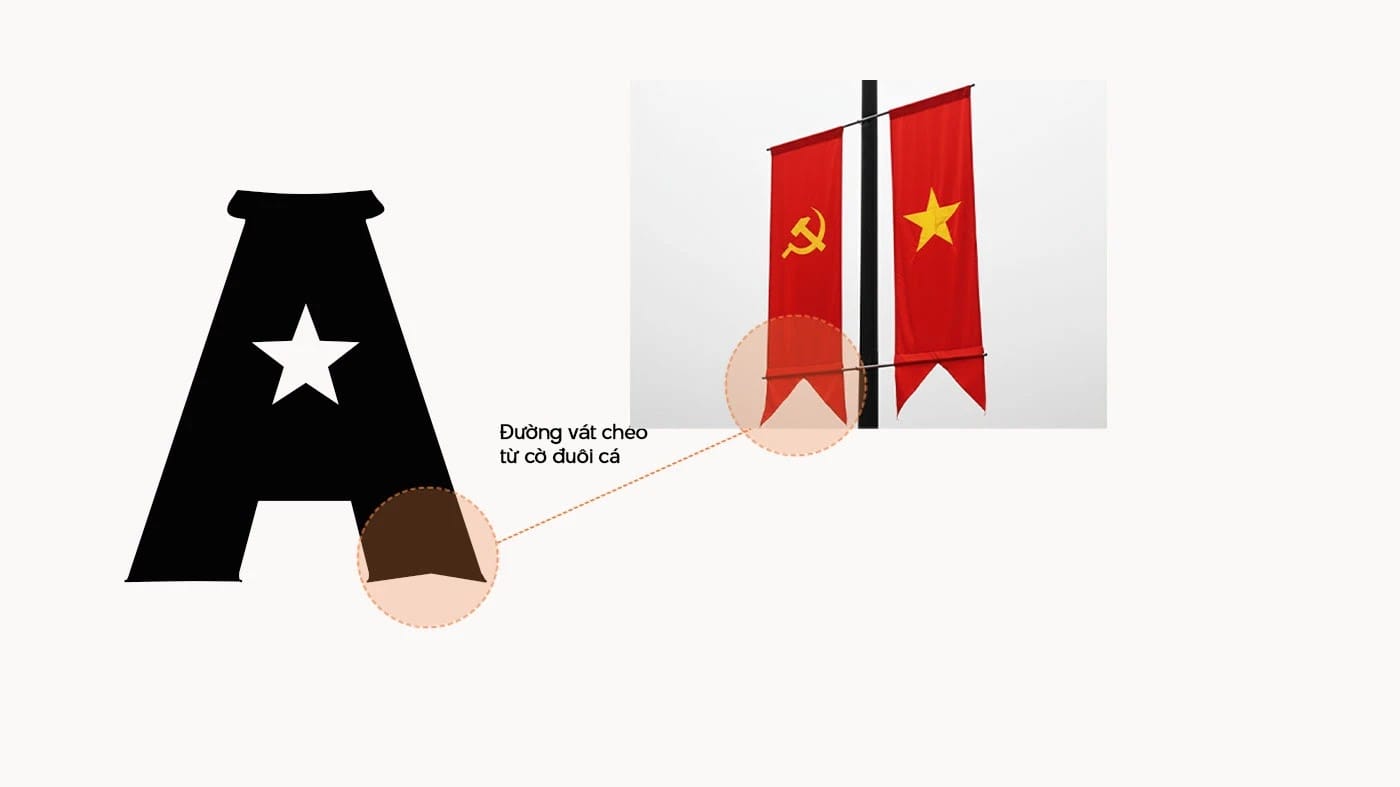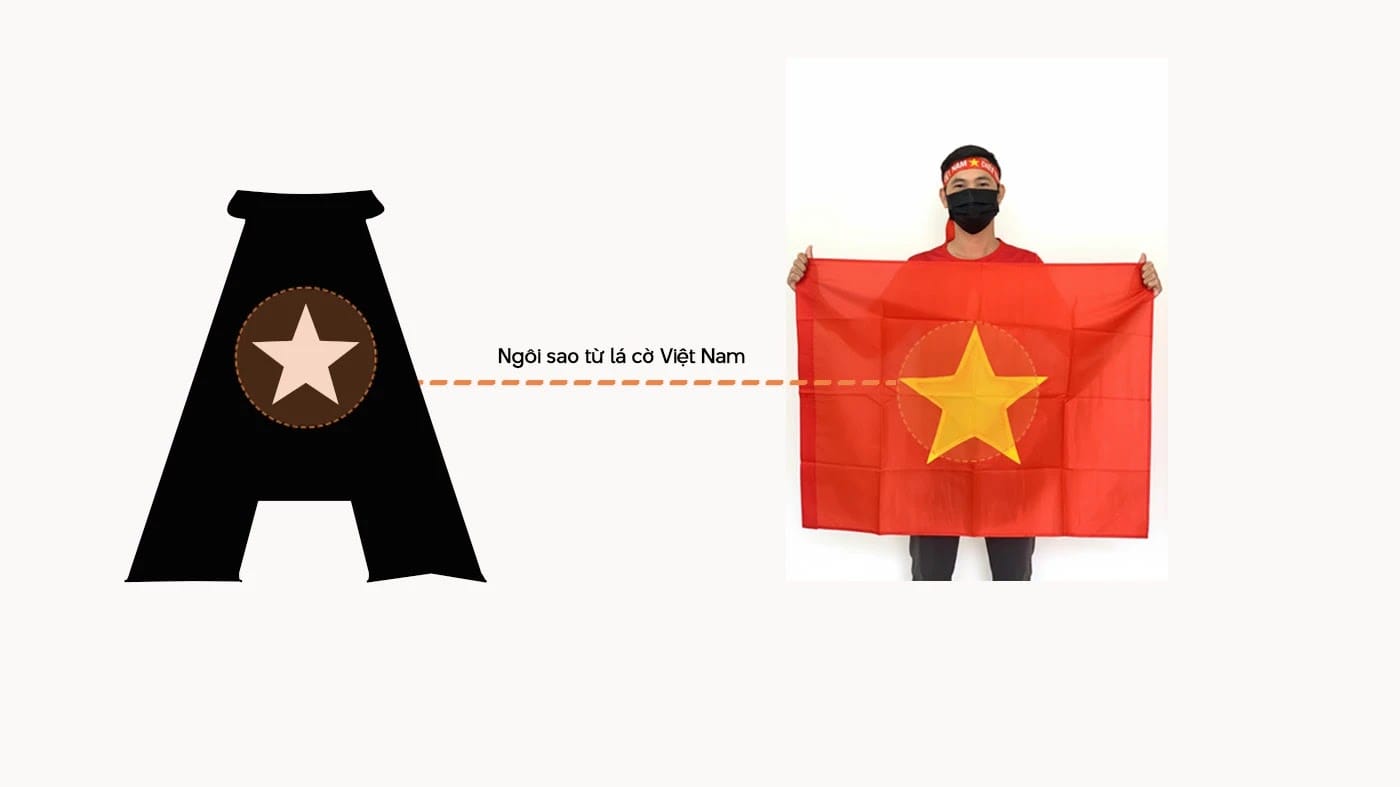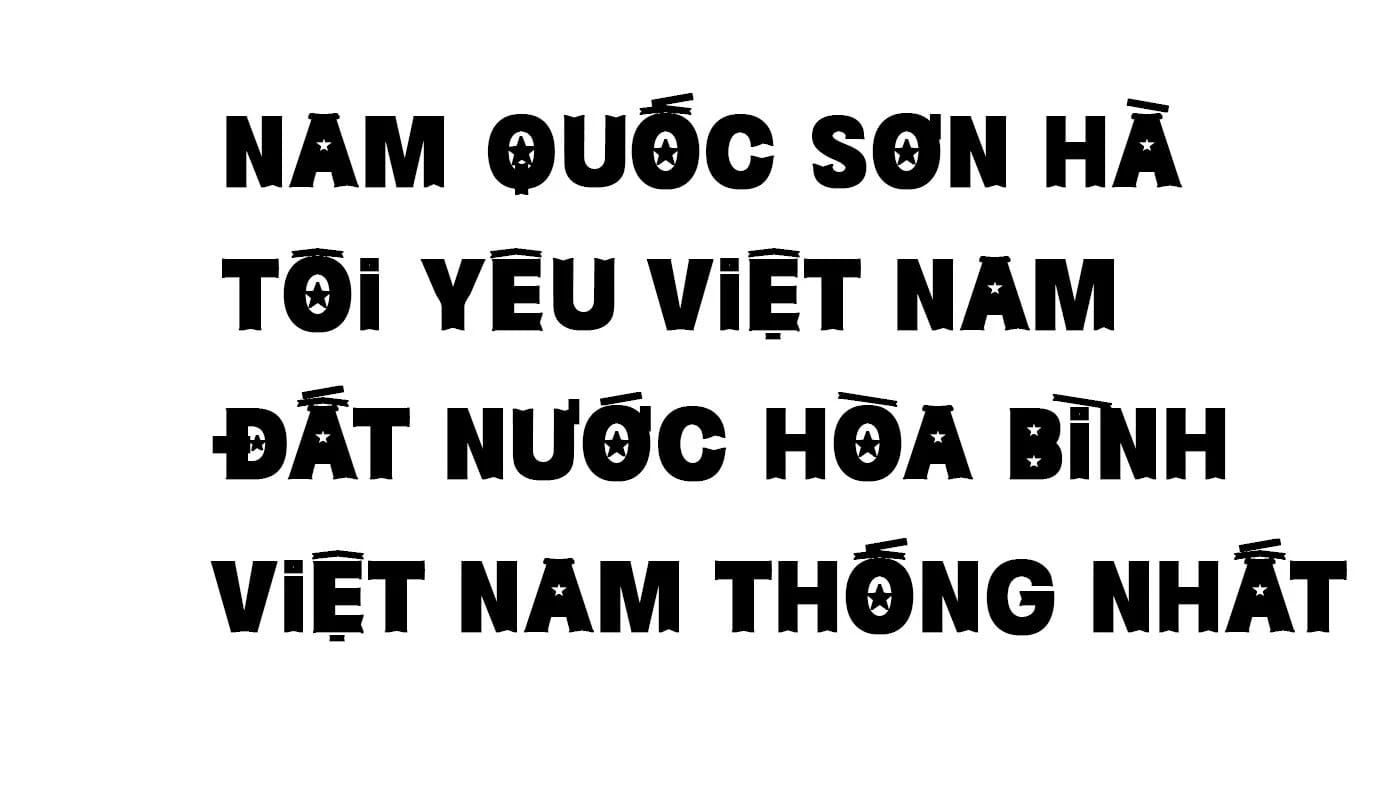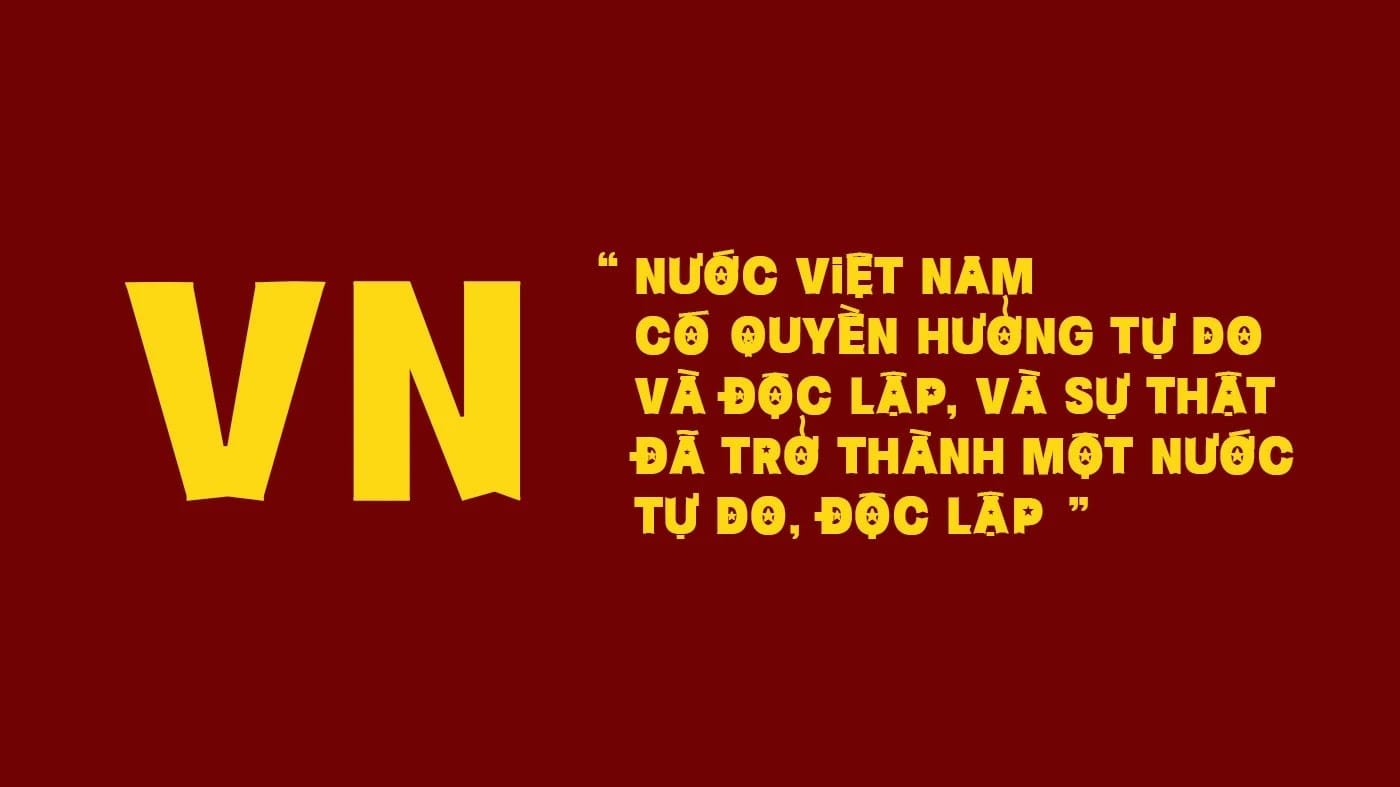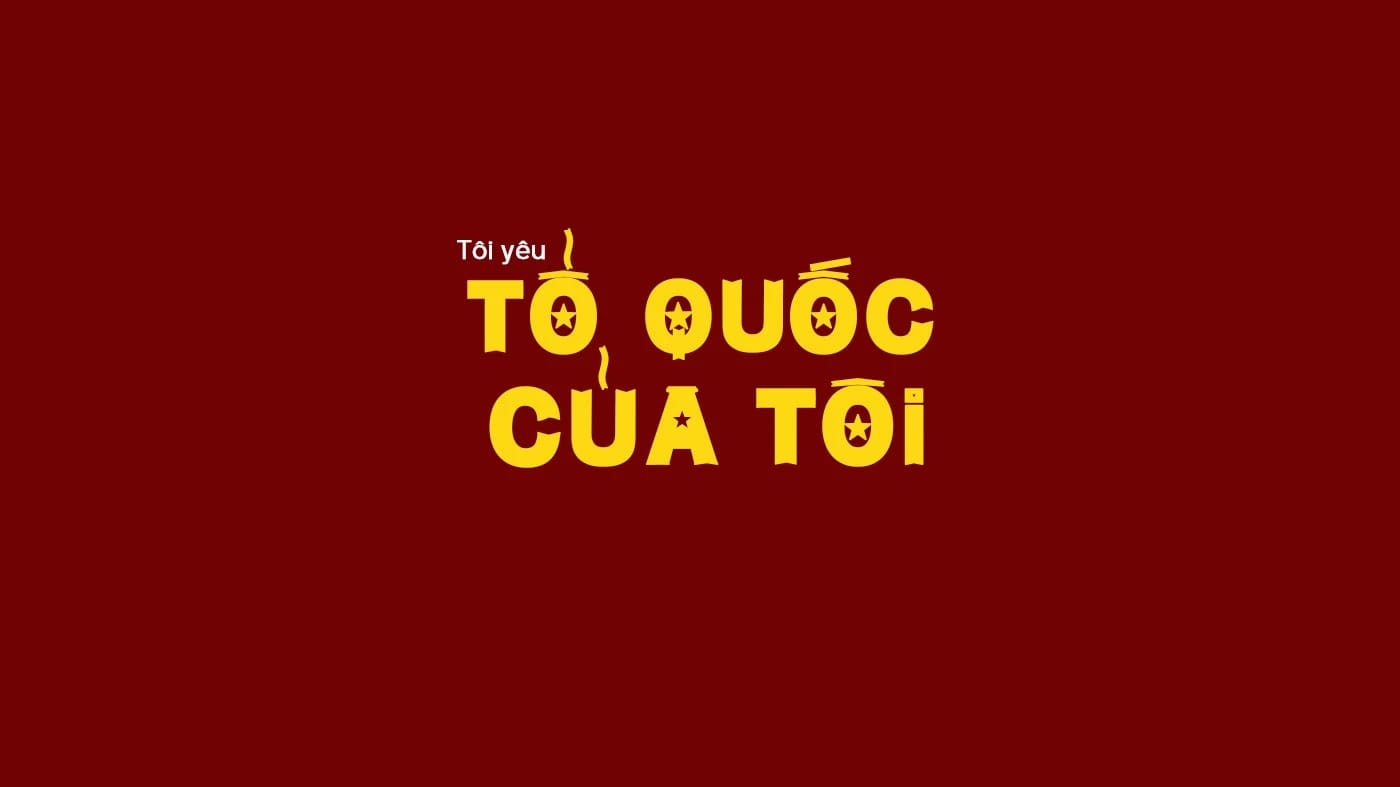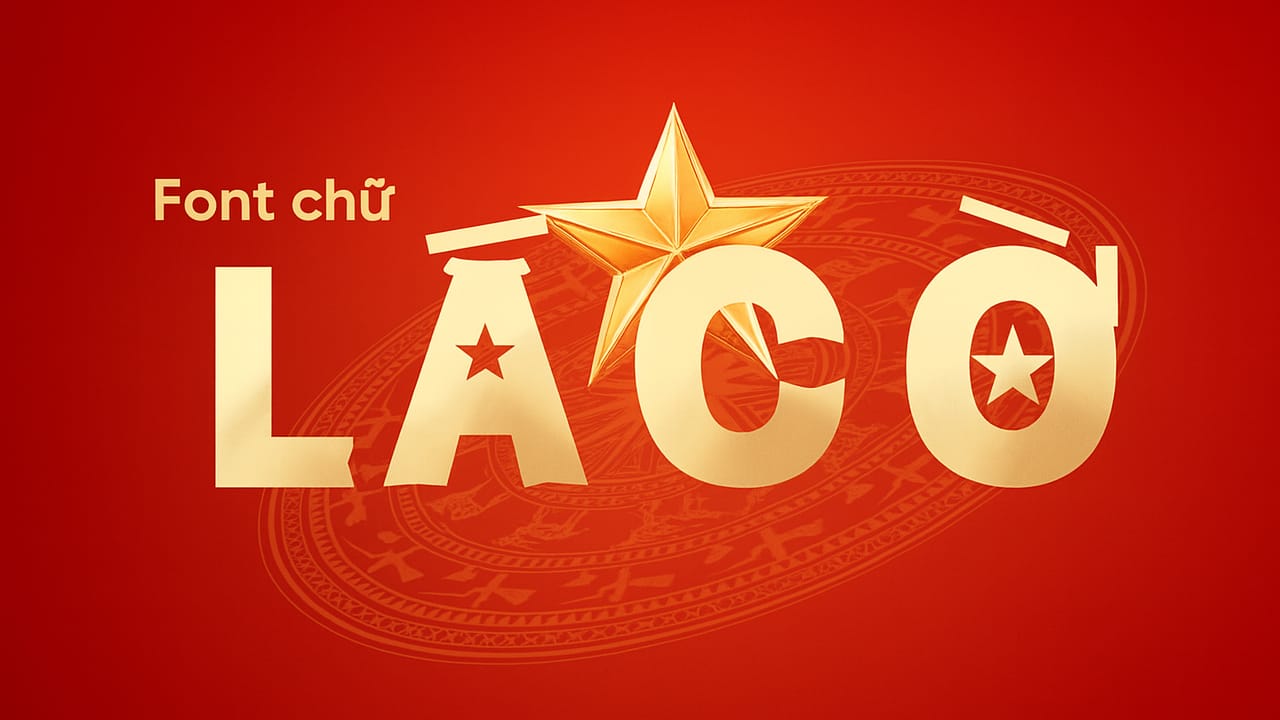
Font tiếng Việt Lá Cờ được lấy cảm hứng từ hình ảnh cờ đuôi cá truyền thống Việt Nam với hình ảnh Ngôi sao vàng là biểu tượng của toàn thể nhân dân Việt Nam cùng đoàn kết một lòng vì Tổ quốc. Năm cánh sao đại diện cho sĩ, nông, công, thương, binh – năm lực lượng chủ chốt chung sức xây dựng và bảo vệ đất nước – những biểu tượng gắn liền với tinh thần đoàn kết, niềm tự hào dân tộc và sức sống bền bỉ.Font chữ mang tinh thần phóng khoáng và nhịp điệu uyển chuyển từ dáng cờ bay, đồng thời được tinh giản trong tạo hình để phù hợp với thẩm mỹ thiết kế đương đại. Typeface này mở ra một phong cách mới mẻ, gần gũi đồng thời có thể gây ấn tượng mạnh mẽ trong các ấn phẩm văn hóa và sáng tạo.Font được thiết kế bởi Nguyễn Thành và được chia sẻ miễn phí cho mục đích cá nhân và thương mại.